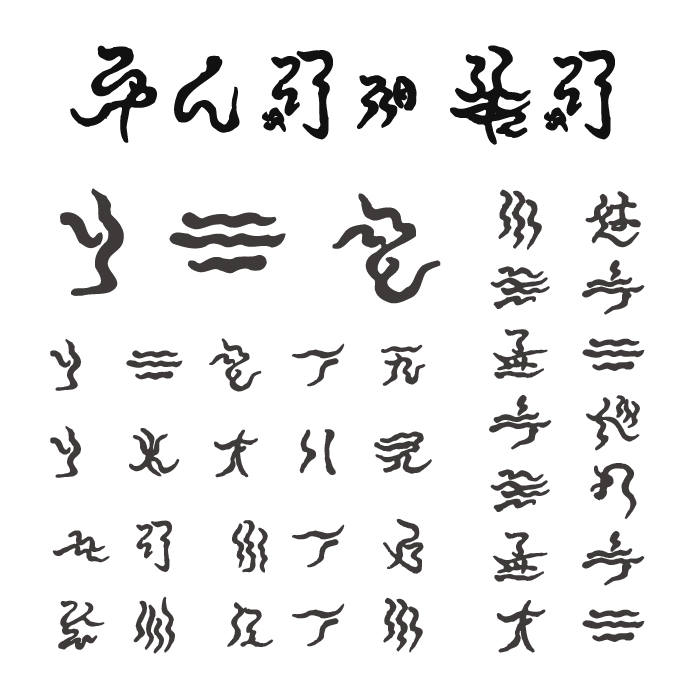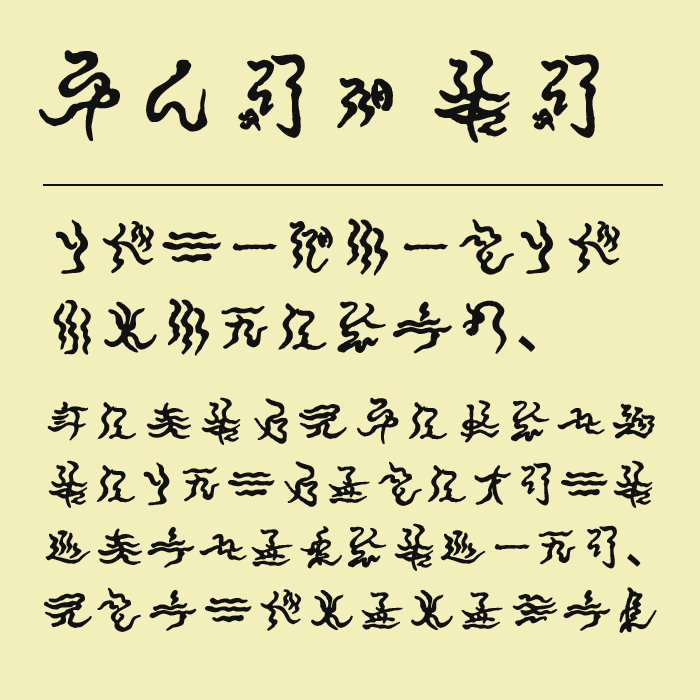
忍者フォントは、漢字が伝来する以前に存在したと言われている「神代文字」という文字をベースに制作されたデザインフォントです。
文字の判読性よりも雰囲気を重視しており、世界観を一気に非日常へ引き込む力があります。忍者・妖怪・時代劇など、古文書や忍術書を彷彿とさせるデザインとして世界観を表現する際にぴったりなフォントです。
フォントの文字見本
収録文字は、ひらがな・カタカナ・記号が収録。